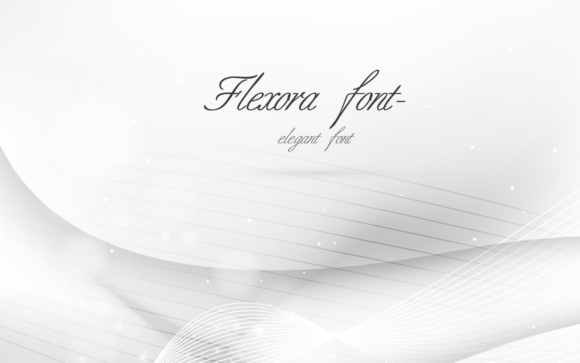
Flexora
適切なデザイン要素を見つけるのは難しい場合がありますが、Flexoraは作品を即座に引き立てる優れたコレクションを提供します。
精密に作られたFlexoraは、クリーンなベクター、滑らかなタイポグラフィ、そして安心のための商用ライセンスを提供します。
POD(オンデマンド印刷)製品、結婚式の招待状、またはソーシャルメディアのグラフィックを作成している場合でも、Flexoraは理想的です。